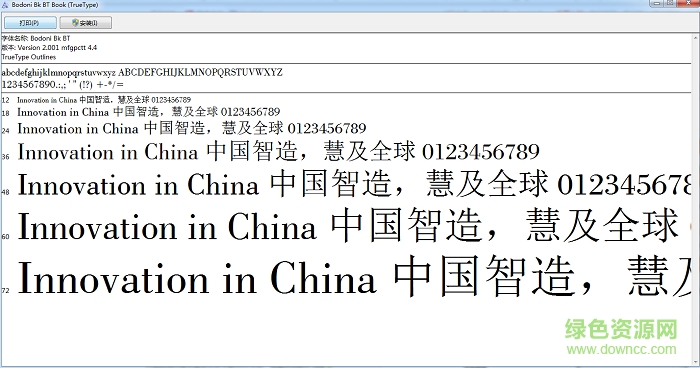
bodoni bk bt普通體
襯線字體介紹
粗襯線(Slab Serif)又稱埃及體:Rockwell 、Courier、Clarendon
現(xiàn)代襯線體(Modern):Didot、Bodoni 、Century、Computer Modern
舊式襯線體(Old style):Adobe Jenson、Janson、Garamond、Bembo、Goudy Old Style
過渡襯線體(Transitional)又稱巴洛克體:Times Roman、Baskerville